(유튜브 요약정리)범죄자와 부자의 글씨체는 다르다? 필적학자가 말해주는 글씨체와 성격과 인생 | 역대 대통령들 필적 분석 | 합격을 부르는 글씨체는 뭘까? (구본진 필적학자) [이강민의 잡지사]
- 필적학자 구본진은 글씨를 통해 성격과 내면을 판단하며, 변호사로 주로 활동한다.
- 글씨체 분석을 통해 성공한 사람들의 공통된 특징을 발견하고, 글씨를 교정하면 인생도 바뀔 수 있다는 주장을 한다.
- 글씨체를 통해 범죄자의 성격을 파악하는 연구가 있으며, 글씨 특징이 범죄 유형과 매칭된다고 한다.
필적학자 구본진의 활동 분야는?
구본진 씨는 국내 1호 필적학자로 알려져 있고, 글씨로 성격과 인생을 읽는다고 해요.
필적학자는 글씨의 크기, 기울기, 간격 등을 분석해 성격과 내면을 진단하고 코칭하죠.
구본진 씨는 변호사로 활동하며, 필적학자로서는 책 인쇄료, 방송 출연료, 강의료 등으로 소득을 얻는다고 해요.또한, 성공한 사람들의 공통된 글씨 특징을 분석하고 글씨 교정이 인생을 바꿀 수 있다고 말하죠..
- 구본진 씨는 국내 1호 필적학자로 알려져 있으며, 글씨를 분석해 사람의 내면과 성격을 알아볼 수 있다고 설명한다.
- 필적학자는 글씨의 크기, 기울기, 간격 등의 특징을 분석하여, 그 사람의 성격과 내면을 진단하고 코칭한다.
- 구본진 씨는 주로 변호사로 활동하며, 필적학자로서 수입은 책 인쇄료, 방송 출연료, 강의료 등으로 드문드문 얻는다.
- 1988년에 사법시험에 합격하고, 군 법무관을 거쳐 21년 동안 검사로 일했으며, 현재는 7년째 변호사로 활동 중이다.
- 필체 분석을 통해 성공한 사람들의 공통된 글씨 특징을 발견하고, 글씨를 교정하면 인생도 바뀔 수 있다는 주장을 한다.
글씨 수집에서 인식 변화?
20년 이상 검사 변호사로 활동하며, 자필 진술서 중요성, 글씨와 범죄 관련성에 흥미를 느꼈어요.미국에서 미술관 방문을 통해 수집과 기증을 인상받고, 한국 복귀 후, 독립운동가의 글씨 수집에 전념했죠.
독립기념관, 국립중앙박물관에서 가장 많은 독립운동가의 글씨를 소장하며, 친일파의 글씨도 수집했어요.친일파의 글씨를 수집하다가 동계 붙는 호칭에 대해 인식을 새롭게 한 것으로 드러냈어요..
글씨체로 범인 분석
글씨 분석을 통해 범죄자의 성격을 파악하는 연구가 있어요.글의 특징이 범죄 유형에 따라 다르며 필체의 특성과 매칭돼요.
희대의 연쇄살인마 유영철의 글씨는 단정하고 또박또박하여 필압이 강하고, 충동적이지 않아서 정신적 또는 육체적 에너지가 강하다는 점이 도드라져요.물론 "그 글씨 분석 안 맞아,유영철 글씨 봐" 라는 반대 의견도 있지만, 필압이 강한 유영철의 필체가 살인자 특성을 나타낸다고 언급돼요..
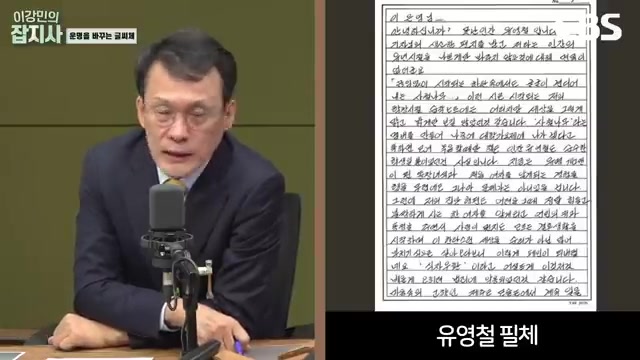
필압과 글씨체의 심리학
필압이 약한 사람들은 범죄 경향이 적어요, 필압이 강하면 신중하고 계획적일 수 있죠.글씨체에서 충동성과 계획성 차이를 파악하며, 이는 내면과 외면의 사람 특징을 반영해요.
글씨체 연구에서 얼굴보다 더 많은 정보를 얻을 수 있고, 글씨를 통해 새로운 면을 발견할 수 있어요..
글씨체가 주는 정보와 성격의 연관?
글씨체 분석시 중점적으로 보는 부분은 크기, 기울기, 간격, 자음과 모음 사이 간격, 단어 간격, 여백, 시작 방법, 전체 기울기 등이며, 가짓수가 다양해요.글씨가 작을 때의 성격은 정확하고 치밀하며 소심하며 보수적 등으로 나타날 수 있고, 둥글둥글한 글씨는 부드럽고 평화를 좋아하는 성격을 보여줘요.필체의 변화가 내면의 변화와 연관이 있는지, 성인이 되면 글씨체는 거의 변화하지 않아요.빨리 쓰거나 예쁘게 쓰는 경우에도 글씨체가 변하지 않습니다.글씨에 대한 측면에서 사람들은 글씨체의 다양성을 강조하지만, 사실 성인이 되면 글씨체는 거의 변하지 않아요..
글씨와 뇌의 연관성 강조된 이유는?
글씨는 뇌의 흔적이라는 독일 필적 학자 플레이어의 말을 통해, 글쓰기와 뇌 활동의 연관성을 강조하고 있어요.'악필'에 대한 관점을 논의하며, 톨스토이, 베토벤 등 천재들도 주로 악필이라는 사실을 언급하고 있어요.악필이 높은 머리를 따라가지 못하면서 나타나는 현상을 설명하며, 자신감 부족으로 인한 글씨 개발 탄압 의문을 제기하고 있어요..
글씨로 유명인 판단하는 방법은?
한글은 어려워서, 한국인들이 대부분 글씨를 잘 못쓰는 경향이 있어요.대통령들의 필체를 비교할 때, 기호성과 힘의 강약이 드러나요.
이승만 전 대통령의 글씨는 유려하고 섬세한데, 박정희 전 대통령은 단단하고 힘이 강한 편이에요.글씨체에서 인격이나 성품을 짐작할 수 있는데, 이승만은 유구하고 부드러우며, 박정희는 근엄하고 강인한 인상을 줍니다.
김연아 선수 필체 특징은?김연아 선수의 필체는 호쾌하고 통이 크며, 미음자 작고 ㅎ 꼭지가 길어 인내심과 최고가 되려는 강한 의지가 돋보이죠.글씨 분석을 통해 김연아 선수와 아사다 마오를 비교했을 때, 김연아 선수는 인내심과 의지가 뚜렷히 드러났고 적수가 될 수 없다고 느꼈어요.김연아 선수의 필체 분석이 굉장히 정확하며, 그의 성품과 열정을 보여주는 부분이 많다고 판단됩니다..
글씨체로 성격과 성공을 탐구하는 방법?
글씨체로 성격과 성공을 분석하는데, 성공하는 사람들의 공통점은 가로선이 길고 우상향하는 특징이에요.성공한 사람들은 다양한 성격을 가지고 있으며, 골프와 야구 선수의 글씨체도 각각 다른데, 야구 선수들은 정밀한 행동이 요구되기 때문에 더 혹해요.재벌들의 필체에서도 특이한 패턴이 나타나는데, 재벌 시리즈를 통해 해당 분석을 진행했어요.성공의 다양한 사례들을 들며, 베토벤, 테레타순, 김수환 추기경, 이승만 등 다양한 성공 사례를 소개해요..
골프 선수들의 글씨와 성공의 연관성?
골프 선수들은 글씨를 통해 성공 특징을 보여주는데, 세계적인 부자들의 글씨와 관련이 있어.글씨의 성공 요소는 긍정적인 낙천적 특징과 인내력을 강조하며, 절약과 결단력을 함께 나타낼 거야.
최고의 글씨는 이병철, 정주영, 마윈 등 세계적인 부자들의 글씨로, 거의 토클래스 수준이래.글씨에 나타나는 특징은 인내력, 긍정적인 사고, 결단력 등을 나타내며, 성공한 사람들 사이에 일치하는 지점을 주는군요..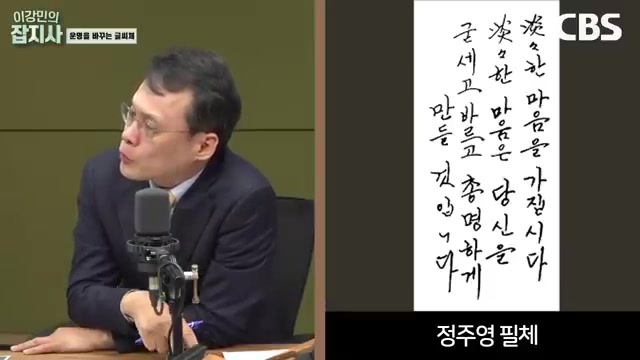
글쓰기의 미래적 의미는?
세로라인을 길게 쓰면 일을 잘 하는 관련성이 있고, 수평선을 길게 쓰면 인내심이 강해진다요.글씨와 기업의 발전, 주식 상승과 연관을 두며 글자로 인생을 변화시킬 수 있다고 강조했어요.
긍정적 사고와 미래를 갖춘 글씨의 중요성을 강조하며, 재미있게 종이에 쓰면서 실제로 효과를 확인할 것을 권유했죠..
필체의 중요성과 조절 방법
대인관계에서 경직된 필체보다 부드러운 필체를 권장해요.글씨체에 따라 의사전달이 어려울 수 있으며, 자음과 모음 사이 간격 조절이 중요하죠.
합격을 부르는 필체, 타로카드집 필체 등이 있으며, 수험생은 글씨를 작게 쓰는 것이 유리해요.글씨에서 'ㄹ'이나 리을의 가로선 색과 간격을 일정하게 유지해야 논리적인 표현이 가능한 거죠..
글씨체와 성격의 관계
글씨체가 소통의 수단이므로 읽을 수 없는 글씨는 피해야 해요.우하향하는 글씨는 우울증의 가능성을 증가시키며, 우울증 환자는 오른쪽으로 글을 짧게 작성하면 치료에 도움이 되요.
오른쪽 아래로 내려가는 글씨를 쓰는 사람들이 주로 자살할 가능성이 있고, 우상향하는 글씨가 바람직하다고 하죠..
글씨 비교: 결론이 뚜렷했던 이유는?
섭외 확인 때 의문을 품었지만, 설득력 느껴졌어요.두 참여자의 필체 비교 위해 애국가 부분을 비교할 거예요.
첫 번째 게스트는 글은 아기자기하고 작지만 현실감각을 갖춰 보였어요.이 참여자도 미음 자를 타듯이 쓰며, 절약적인 느낌을 줬죠..
글씨 분석의 결과는?
글씨를 통해 낭비를 싫어하고 절약과 자신감이 보여요.글씨 간격과 형태로 심리적 특성을 파악하며, 곽재식 작가와 일치함을 발견했어요.
대학을 잘 마치고 욕심 많은 성격을 보이며, 말더듬이 뉴스 전도사와 유사한 점을 지적했죠..
글씨 속성 분석 : 미래, 자아 인식, 재물, 글씨 예술성에 대한 명상
- 글씨 속의 성격, 모티브, 재물 손실 등을 분석
- 성향 예측을 통한 글씨 간격, 특징 등 상세히 설명
- 인물 특성, 글씨 예술성과 최근 노력 등 관찰
- 유명 인사들의 글씨와 글씨 연습의 중요성 강조
- 유튜브 현판 글씨 사용과 글씨 분석의 목적 제시
위 유튜브 내용을 통하여 필체의 특징을 아래에 요약해 봅니다.
- 글씨체를 통해 성격과 성공을 분석하는데, 성공하는 사람들의 공통점은 가로선이 길고 우상향하는 특징이다.
- 글씨체의 가로선이 길고 우상향인 경우, 성공적인 사람들의 특징을 나타낸다.
- 이는 성공한 사람들이 다양한 성격을 지니고 있음을 시사한다.
- 재벌들의 필체에서도 특이한 패턴이 나타나는데, 재벌 시리즈를 통해 해당 분석이 진행되었다.
- 성공의 다양한 사례들을 들며, 베토벤, 테레타순, 김수환 추기경, 이승만 등 다양한 성공 사례를 소개한다.
▶ 글씨로 미래를 설계하고, 세로라인을 길게 쓰면 일을 잘하는 관련성이 있으며, 수평선을 길게 쓰면 인내심이 강해진다.
- 글자로 인생을 바꿀 수 있다는 주장에서 글씨의 중요성을 강조한다.
- 글씨와 기업의 발전, 주식 상승과의 연관성을 두었으며, 긍정적 사고와 미래를 반영한 글씨의 중요성을 강조한다.
- 대인관계에서의 필체 중 부드러운 필체를 권장하며, 글씨체에 따라 의사전달이 어려울 수 있음을 강조한다.
▶글씨체가 소통의 수단이므로 읽을 수 없는 글씨는 피해야 한다.